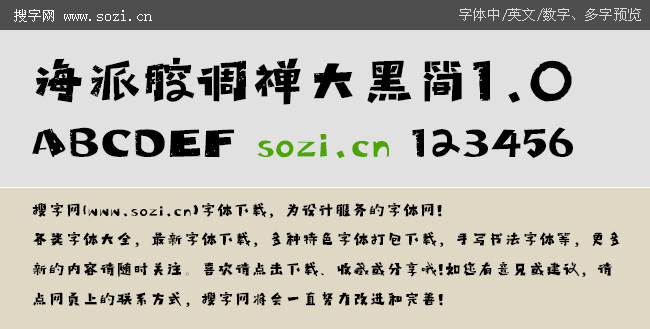
海派腔調(diào)禪大黑簡1.0
搜字網(wǎng)提供一海派腔調(diào)禪大黑簡1.0中文字體下載,海派腔調(diào)禪大黑簡字體是一款左粗右細(xì)、整體效果非常出眾的簡體中文字體,適合應(yīng)用于廣告設(shè)計(jì)、名片設(shè)計(jì)、包裝印刷、產(chǎn)品設(shè)計(jì)等應(yīng)用。